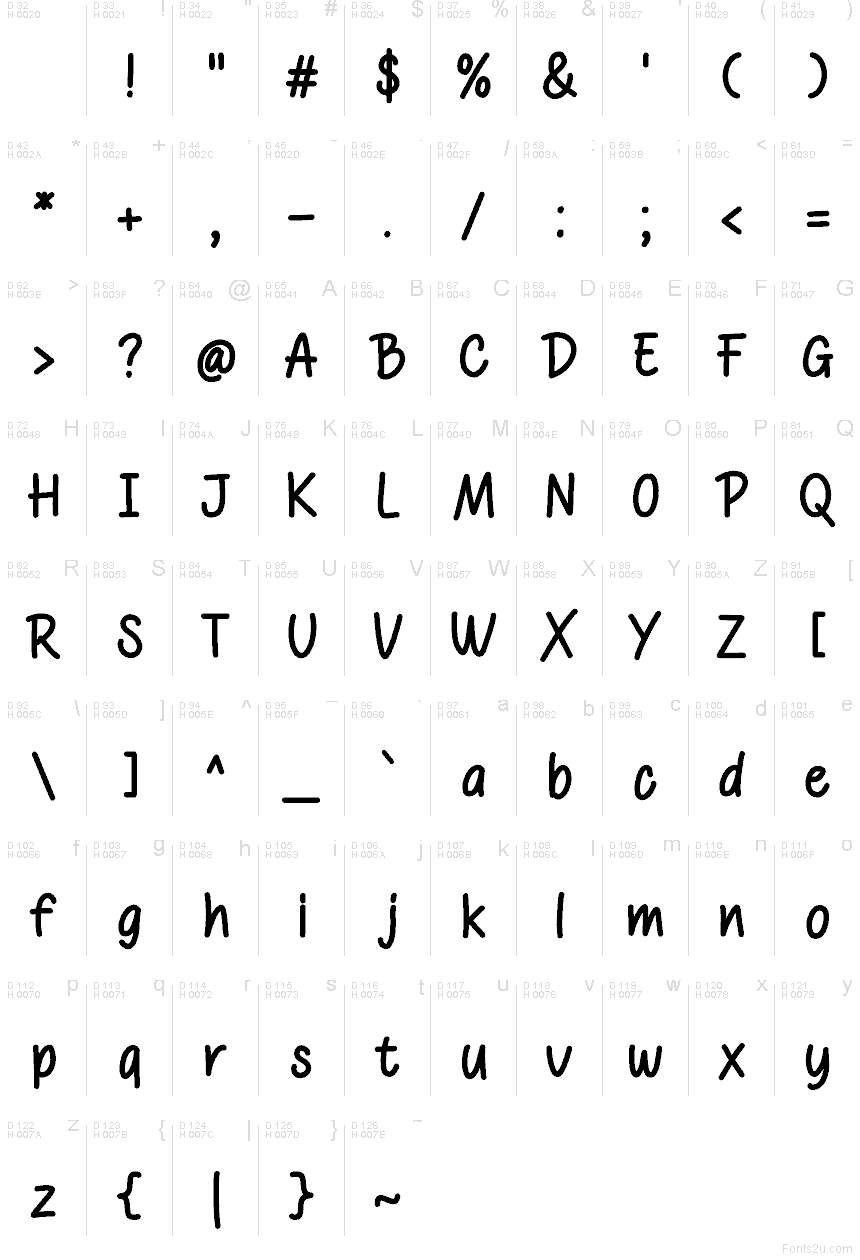
Written Good
Written Good est une police manuscrite gratuite aux tracés arrondis et irréguliers. Son rythme décontracté, façon marqueur, confère aux lettres un aspect vivant et chaleureux. Les formes restent simples et verticales, avec des courbes douces et un fini dessiné à la main qui évoque l'informel sans jamais paraître brouillon.
Written Good est idéale pour les invitations, les visuels de citations, les logos, les publications sur les réseaux sociaux, ainsi que les emballages et étiquettes de produits où la touche personnelle fait toute la différence. La fluidité de son trait apporte une authenticité manuscrite aux textes courts, parfaite pour le branding lifestyle, les projets créatifs et les mises en page éditoriales chaleureuses.